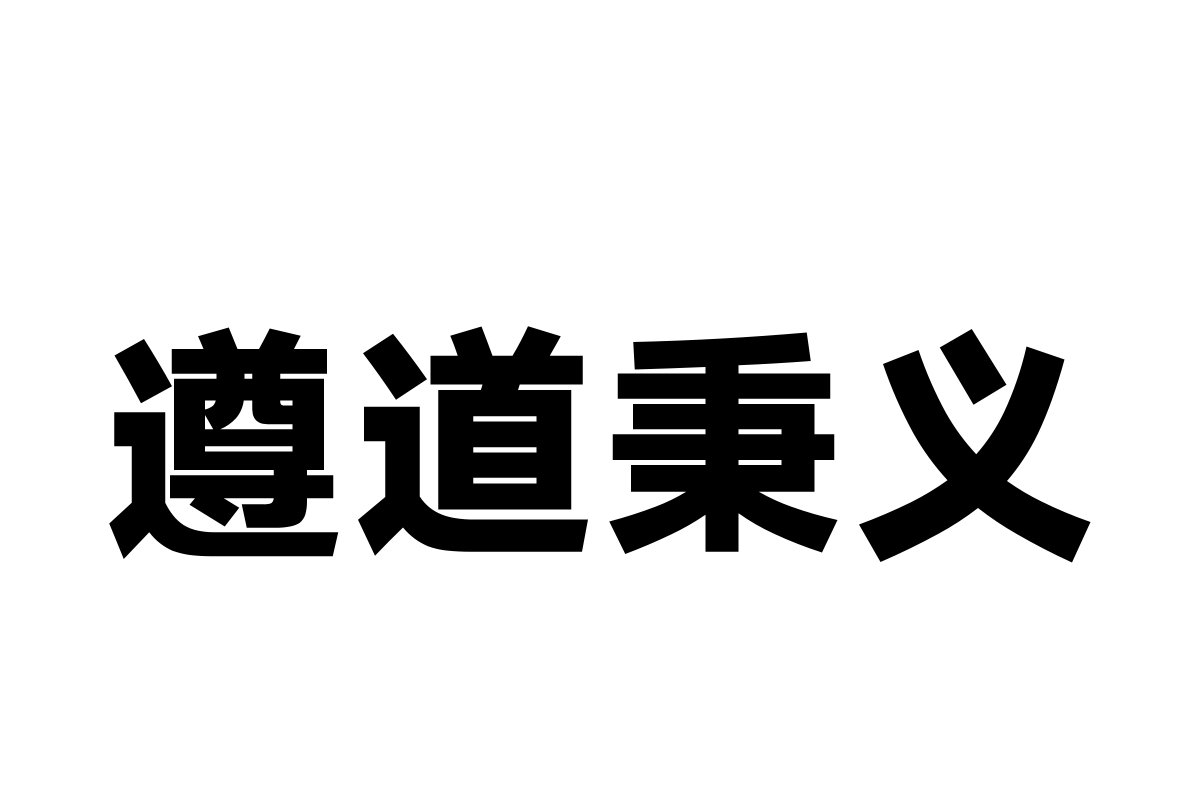
汉仪旗黑-95 是一款具有独特风格的字体,其设计灵感来源于中国传统的旗帜。这款字体采用了简洁、大气的设计风格,线条流畅,结构严谨。在字形上,汉仪旗黑-95 保持了传统旗帜的特点,如竖直的笔画和独特的形状。同时,该字体还融入了一些现代元素,使其更加符合现代人的审美需求。
汉仪旗黑-95 适用于各种需要展示传统文化特色的场合,如广告设计、包装设计、书籍封面等。这款字体不仅能够吸引人们的注意力,还能够传达出庄重、典雅的氛围。